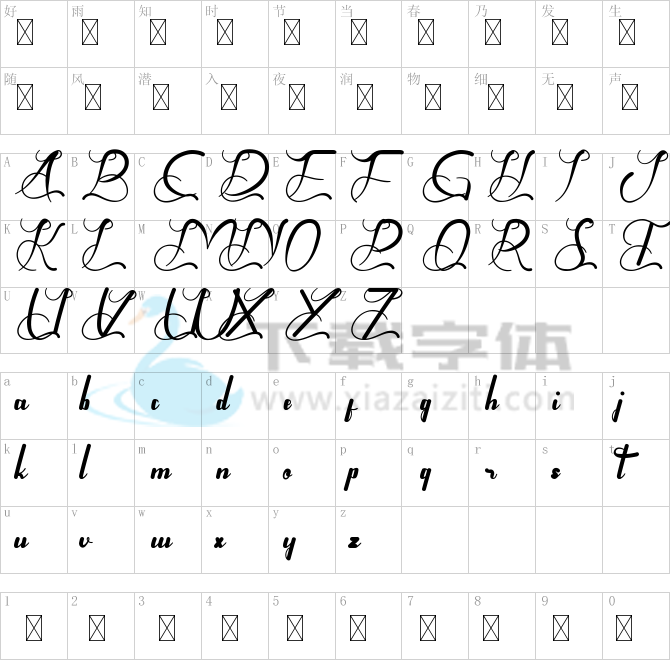
Arrival Demo.ttf字体下载
Arrival Demo.ttf字体下载,这款字体结构工整、笔画清晰,兼顾美观与易读性,适用于标题、正文、海报、包装、LOGO 等多种场景。字形优雅稳定,风格百搭耐看,适配日常排版与创意设计,让文字呈现更舒适、更具质感。Arrival Demo.ttf字体下载一笔一画,皆是细节,以均衡的比例、流畅的线条打造舒适视觉体验,字形端正大气,风格简约现代。无论是商业设计、品牌宣传还是日常排版,都能轻松驾驭,让文字更有格调与力量。Arrival Demo.ttf字体下载字体下载。